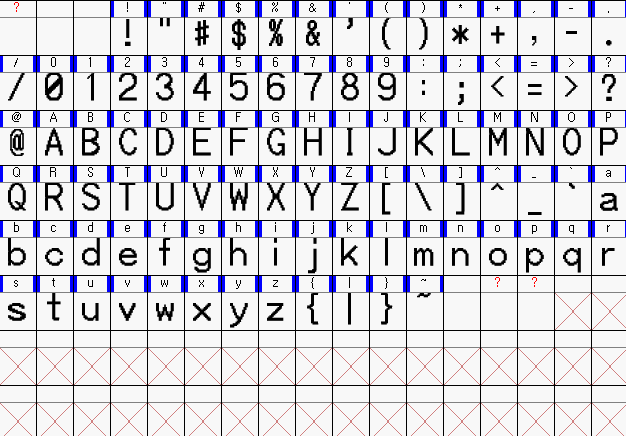
zBar-F
zBar-* series fonts are based on Zebra barcode label printer. The font format is TTF, which is convenient for users to print various labels. Note that the size of the font should be set to 8.5 or a multiple of 8.5 pt.
Contoh hasil cetak (pada label pengiriman):
Contoh hasil cetak (pada label barcode):
Contoh hasil cetak (pada label produk Samsung):
Semua karakter font zBar-F:
Font zBar-F dilihat dengan penampil font bawaan Windows: